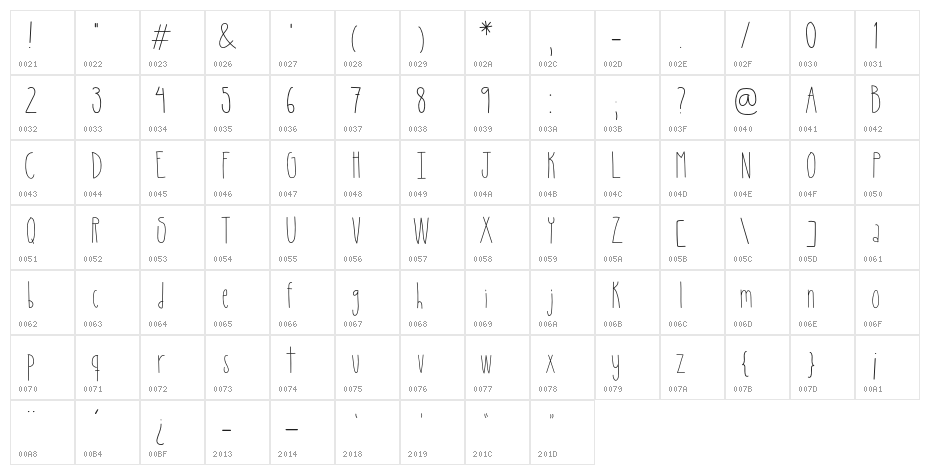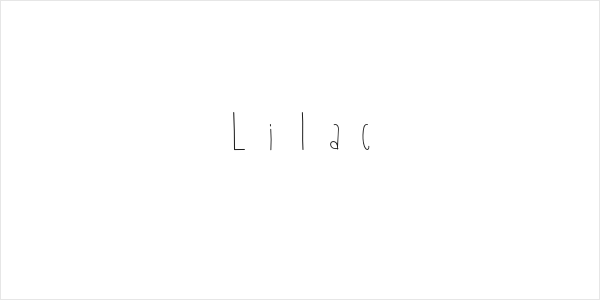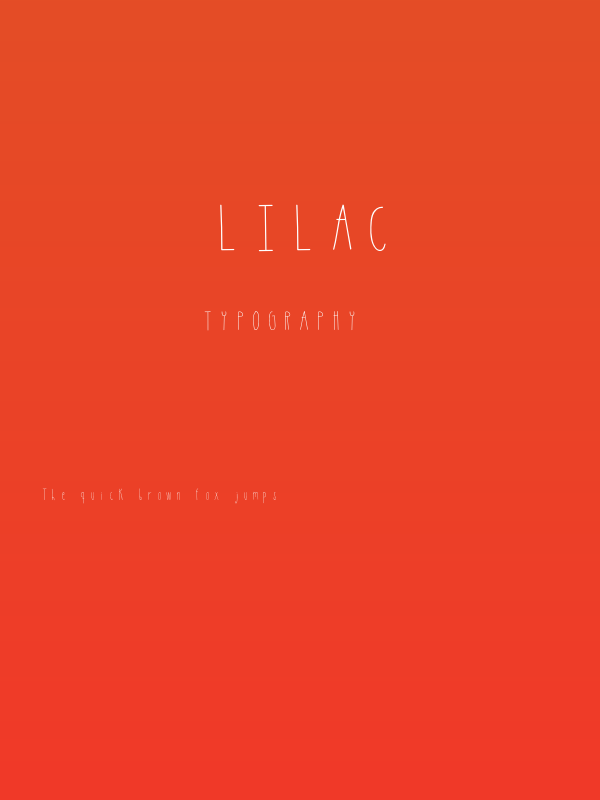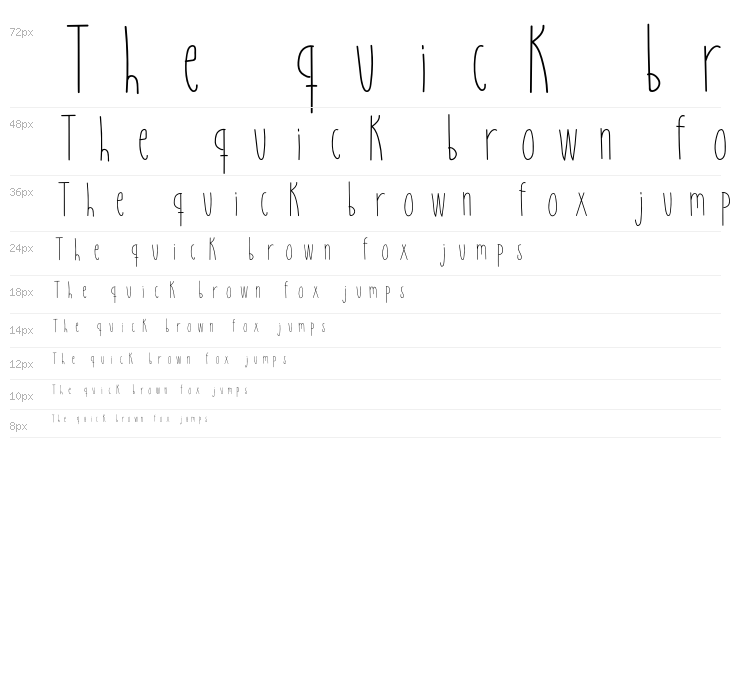
Lilac Font
| Stile generale | Whimsical |
| Caso d'uso | Headlines, Casual text, Invitations |
| Progetti proposti | Ideal for greeting cards, children's books, casual invitations, and playful branding. |